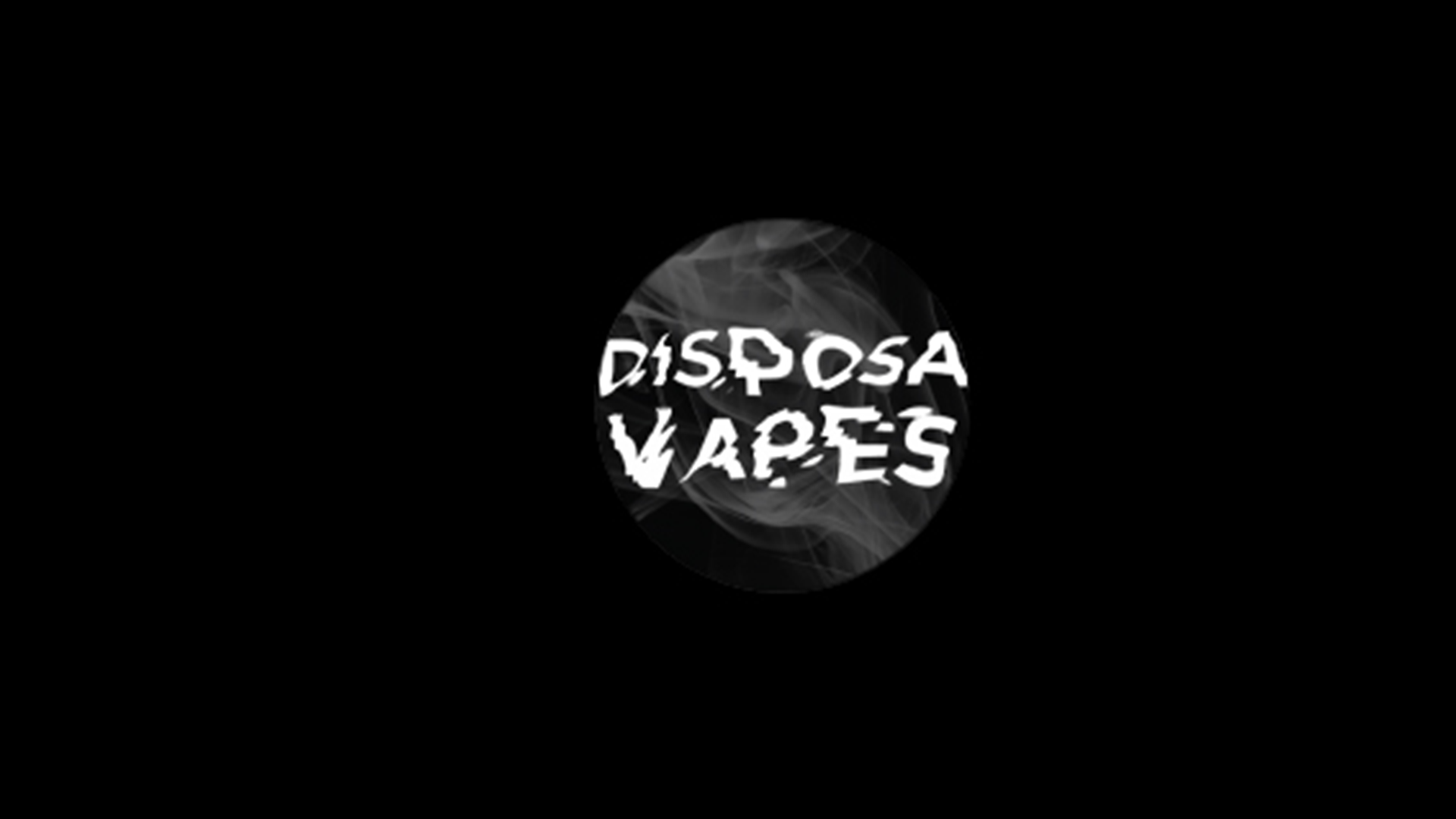
Logo wykonane jest za pomocą Photoshopa, wykorzystując teksturę dymu do wizualnego wyrażania sfery działalności firmy. Praca została wykonana w ramach konkursu. Na freelancerze na placu. #photoshop #socialmarketing #logo #logotype #typography #brending